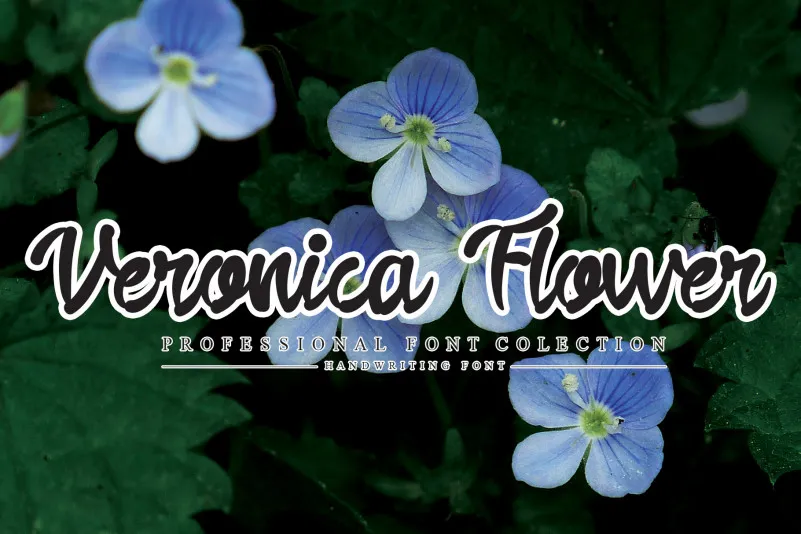
Veronica Flower Script Font – Fonte Grátis
Veronica Flower Script Font
A Veronica Flower Script Font é uma delicada e suave fonte feita à mão. Seus belos e arredondados caracteres a tornam algo realmente encantador. Ela se destaca pela sua versatilidade única, fazendo-a perfeita para criar designs espectaculares. Não hesite em adicionar Veronica Flower Script Font à sua próxima criação – ela certamente vai torná-la ainda mais especial. Idealmente utilizável em textos decorativos, como nomes de empresas ou publicações, a Veronica Flower Script é uma escolha perfeita para quem procura um toque delicado e elegante que se destaca no design gráfico. Seja você designer de logotipos, ilustrador digital ou apenas aquele que adora criar e personalizar designs digitais, você certamente vai encontrar algo incrível na Veronica Flower Script Font.